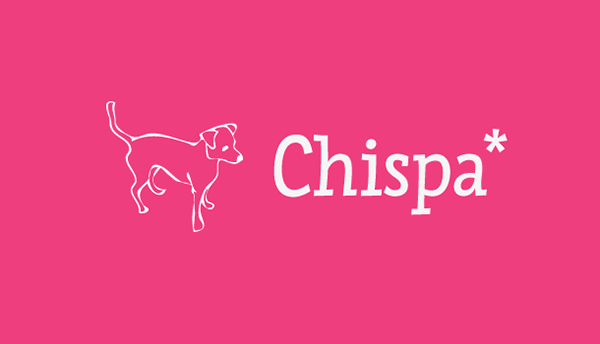
Chispa Font – Download Grátis
A Chispa é uma elegante fonte sans-serif desenvolvida pelo designer Hamilton. Esta fonte é perfeita para projetos atuais e contemporâneos que buscam um visual minimalista, devido à sua simplicidade e clareza. Com linhas finas e sutis, a Chispa se destaca por manter uma proporção equilibrada entre seriedade e modernidade. Ela é perfeita para aplicações digitais que exigem um estilo clean e versátil sem perder em qualidade ou legibilidade. Para mais detalhes sobre a fonte, visite o site da Tipomatica: http://www.tipomatica.com/tipos/chispa.html.